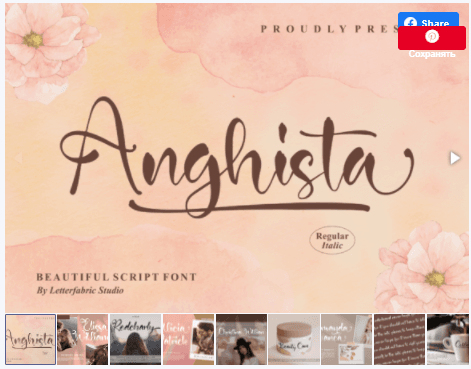
Anghista Beautiful Script Font
Anghista — красивый рукописный шрифт. Он подходит для любых проектов, таких как: логотипы, брендинговые проекты, дизайн товаров для дома, упаковка продуктов, кружки, цитаты, плакаты, сумки для покупок, футболки, обложки книг, визитки, пригласительные билеты и многое другое.